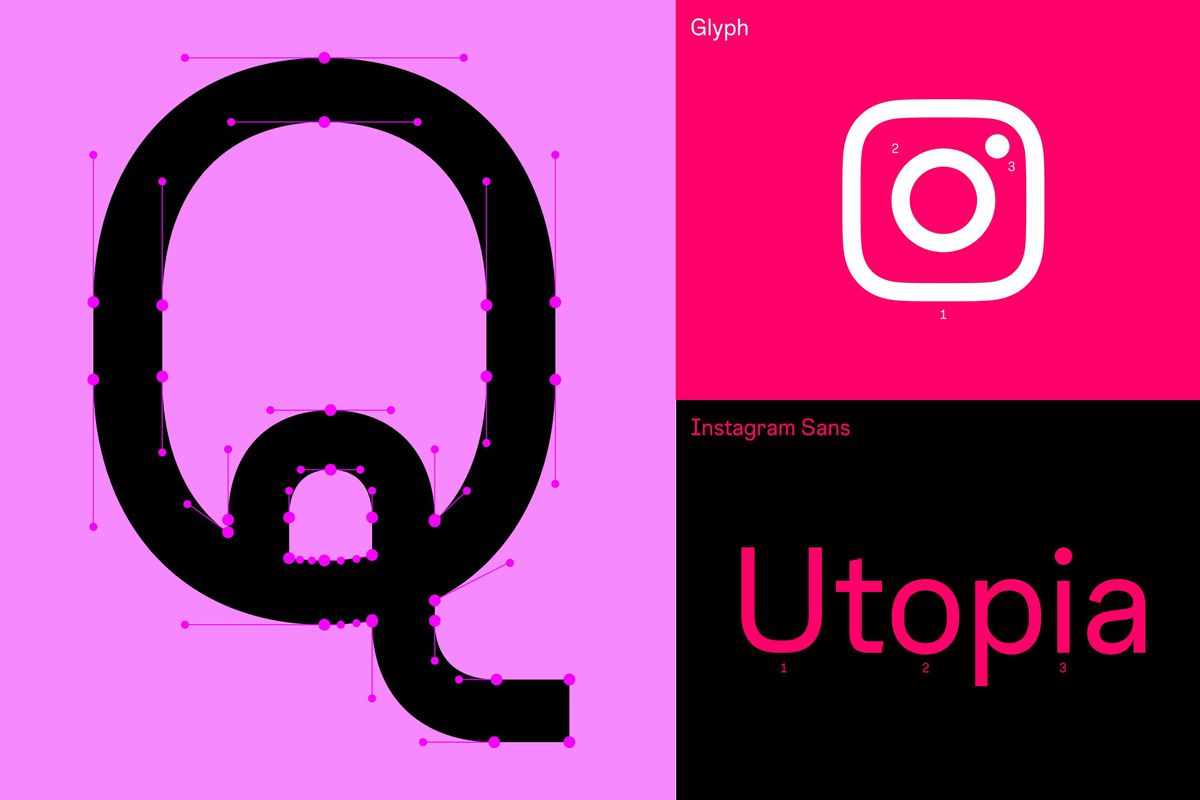
Teknologi.id – Baru-baru ini Instagram mengubah beberapa elemennya di aplikasi. Meski tak terlalu mencolok, namun perubahan ini mencakup pembaruan pada logo yang lebih cerah, font, tata letak, dan aspek desain lainnya.
"Hari ini, kami membawa energi dan tujuan baru ke warna, jenis huruf, logo, dan elemen merek lainnya dengan identitas visual yang segar. Sistem baru kami dirancang untuk merangkul evolusi berkelanjutan untuk membantu kami menciptakan pengalaman yang lebih mendalam dan inklusif bagi komunitas kami," ucap pihak Instagram.
Lalu, jenis font baru yang disebut Instagram Sans dirancang dengan mempertimbangkan warisan platform. Pihak Instagram mengatakan font itu terinspirasi oleh kotak dan lingkaran.
Pihak Instagram mengatakan Instagram Sans adalah remix kontemporer dari gaya aneh dan geometris, serta merupakan cara baru bagi komunitas global untuk mengekspresikan diri mereka di tempat-tempat seperti Stories dan Reels.
Melansir TechCrunch, font baru lainnya yakni Instagram Sans Regular, Bold, Light, Medium, Condensed dan Condensed Bold.
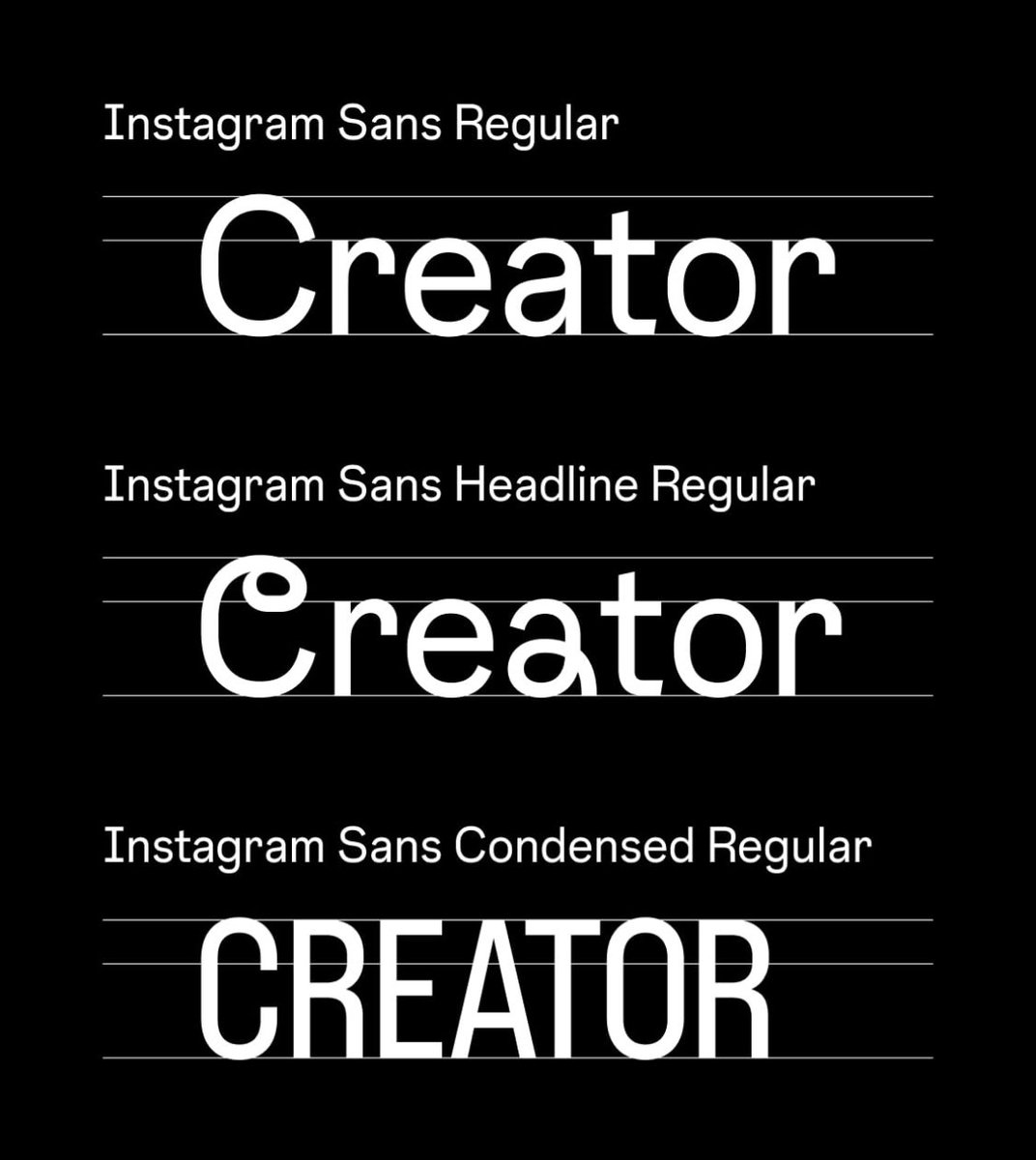
"Kami bermitra dengan pakar bahasa di seluruh dunia untuk mengadaptasi jenis huruf ke skrip global termasuk Arab, Thailand, dan Jepang," ujar Instagram.
"Kami ingin mendukung semua pembuat konten dan anggota komunitas kami yang mendorong budaya untuk mengekspresikan diri mereka sepenuhnya dalam bahasa apa pun yang mereka pilih," imbuhnya.